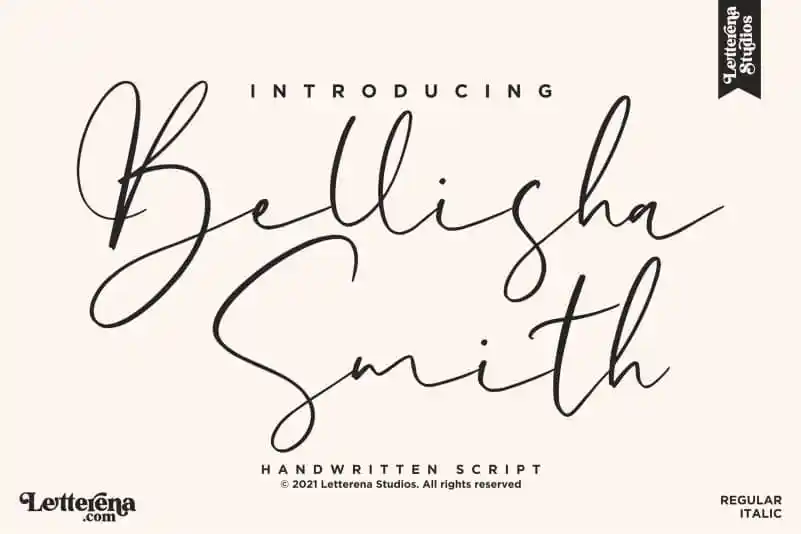
Bellisha Smith Script Font – Download Grátis
A fonte ‘Bellisha Smith Script Font’ da Letterena é uma delícia para os olhos, ideal para qualquer projeto que você possa imaginar. Com sua elegância e romantismo chamado de calligraphie, esta fonte escrita a mão é perfeita para logos, projetos de marca, design de móveis de casa, embalagens de produtos, tigelas de café, frases, cartazes, sacolas de shopping, camisas personalizadas, capas de livros, crachás, convites, cartões de agradecimento e etiquetas. Se você estiver criando algo que mereça um toque especial e luxuoso, seja ele uma marca ou uma peça decorativa, este é o companheiro perfeito para seu trabalho. Ela também se destaca em seus usos menos visuais como um watermark no seu site de vendas online, adesivos especiais na sua festa de aniversário e até mesmo nos registros de eventos exclusivos que você organize. Com a ‘Bellisha Smith Script Font’ da Letterena, suas criações serão sempre elegantes e memoráveis, destacando-se entre os demais.